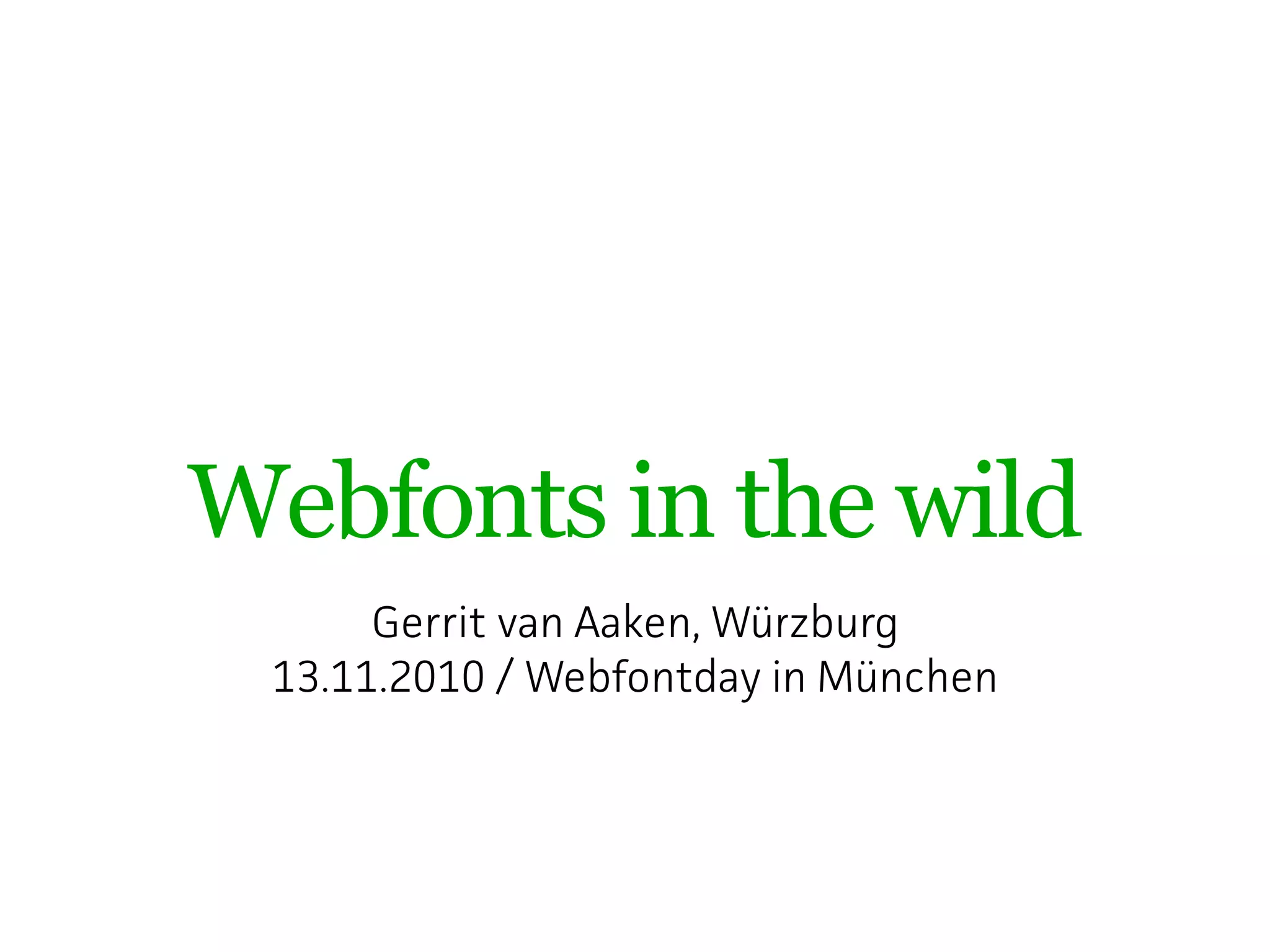
Webfonts in the wild
Gerrit van Aaken, Wüzburg
Typografie
Selbst-
referenziaität!
Die ersten Seiten mit
Webfonts der
„Neuen Generation“
Gaublau
Bello,
Proxima Nova
Liza, Auto
Echte Websites
gehen anders!
Evtl. so?
Museo
Swingdancer,
Droid
Calluna
Feda
KatarineWeb
Skolar
St. Marie,
AdelleWeb
Moment mal …
... das sind ja alles Designer!
So sieht’s aus.
Was fällt auf bisher?
• Layout zupackend oder minimalistisch
– die moderne At, Websites zu gestalten
Was fällt auf bisher?
• Layout zupackend oder minimalistisch
– die moderne At, Websites zu gestalten
• Schriftgad sehr groß
– Websafe Fonts zu klobig ür hohe Schriftgade
Was fällt auf bisher?
• Layout zupackend oder minimalistisch
– die moderne At, Websites zu gestalten
• Schriftgad sehr groß
– Websafe Fonts zu klobig ür hohe Schriftgade
• sehr fette oder sehr magere Schnitte
– bisher kaum mögich
Proxima Nova
Ambroise
Theano,
Share, Chunk
Coquette, P22
Underground
Arial
Titillium
Meta Serif
Tisa
Immer noch …
Woran liegt’s?
Immer noch …
Woran liegt’s?
• Taditionelles Webdesign
Immer noch …
Woran liegt’s?
• Taditionelles Webdesign
• Budget
Immer noch …
Woran liegt’s?
• Taditionelles Webdesign
• Budget
• Windows-User ohne ClearType
Aber es geht doch:
Cheltenham
Adrianne
Museo,
League, Meta
Raleway
These 1
Webfonts lohnen sich vor allem in hohen
Schriftgaden.
These 2
Taditionell gestaltete Websites mit Webfonts
nachzurüsten: oft unbefriedigend.
These 3
Webfonts efordern ein neues
Webdesign-Paadigma.
These 3
Webfonts efordern ein neues
Webdesign-Paadigma.
Moment!
Henne und Ei.
~ 2005
These 3
Webfonts efordern ein neues
Webdesign-Paadigma.
These 3
Das moderne Webdesign-Paadigma
efordet Webfonts
Webfonts vs. Bilder
• Komplexe Kunst-Arangements sind kein
Mehwet ür den Nutzer
Webfonts vs. Bilder
• Komplexe Kunst-Arangements sind kein
Mehwet ür den Nutzer
• Webfonts lohnen sich nicht, wenn das
gleiche Resultat mit Bilddateien
schneller erreicht werden kann.
Webfonts vs. Bilder
• Komplexe Kunst-Arangements sind kein
Mehwet ür den Nutzer
• Webfonts lohnen sich nicht, wenn das
gleiche Resultat mit Bilddateien
schneller erreicht werden kann.
• Fließtext-Check!
Adobe Text
Pater
Bree, Skolar